Типографика играет важную роль в создании элегантного и эстетичного вида для различных типов дизайна. У люксовых брендов типографика занимает центральное место в дизайне упаковки продуктов, а их фирменный стиль широко известен.
Именно шрифты, которые они используют, создают ощущение модернизма, роскоши и эстетики. Вот почему элегантные и эстетичные шрифты довольно популярны в индустрии моды и красоты. В этой статье мы рассмотрим 10 элегантных шрифтов в 2023 году, которые можно скачать совершенно бесплатно.
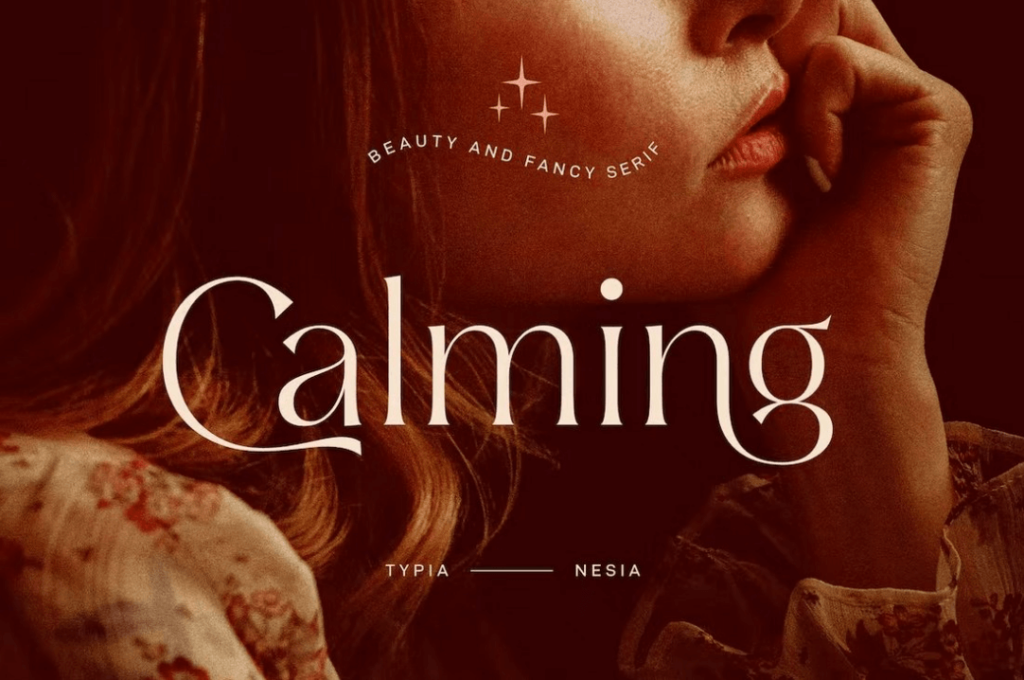
Calming — это красивый и элегантный шрифт, который поможет придать вашему дизайну легкость и индивидуальность. Шрифт идеально подходит для дизайна упаковки косметических продуктов. Вы также можете использовать его для брендинга, постов в социальных сетях и дизайна веб-сайтов.
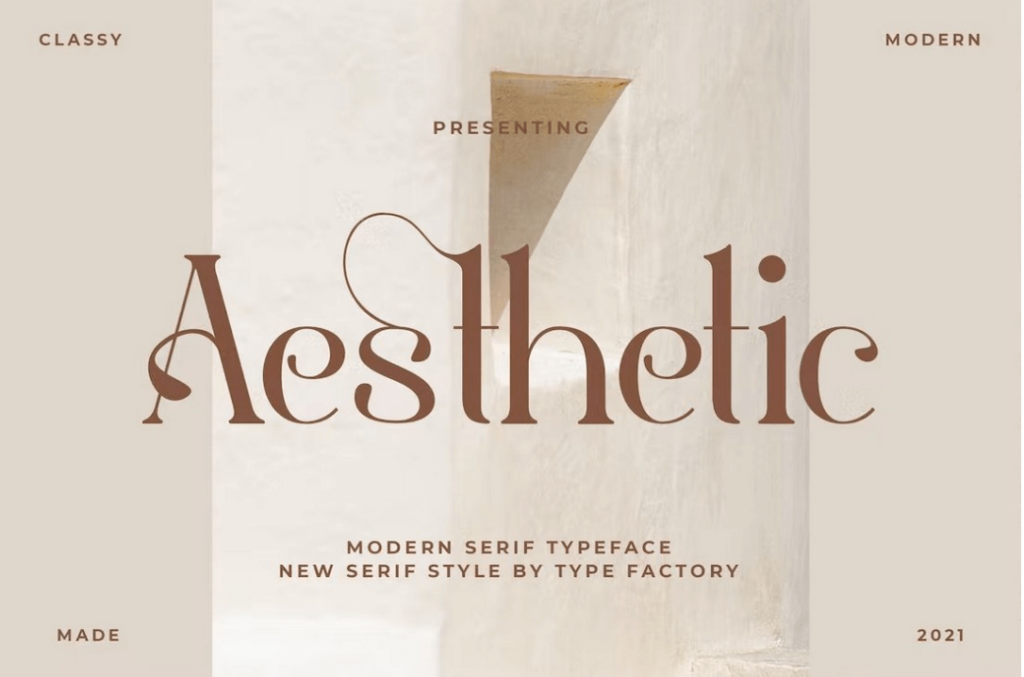
Шрифт Aesthetic имеет современный дизайн букв с засечками, смешанный с уникальными декоративными элементами. У шрифта есть как прописные, так и строчные символы. Вы можете использовать его для брендинга, обложек журналов и других проектов.
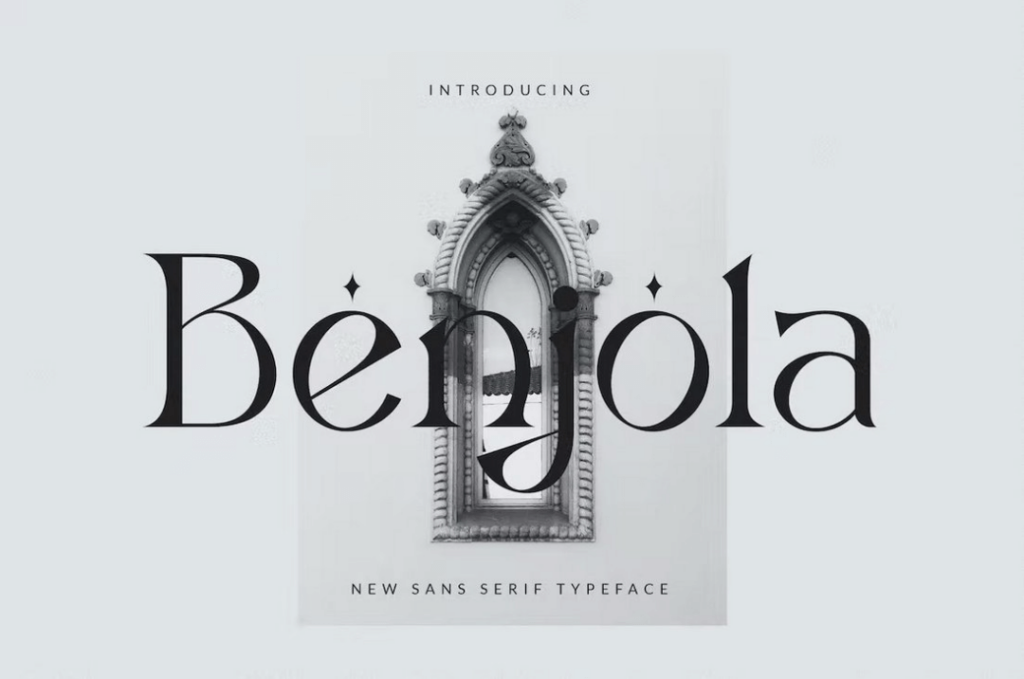
Benjola — это уникальный минималистичный шрифт, который выглядит современно и роскошно. Он поможет сделать логотипы вашего бренда роскошным, а дизайн упаковки или заголовок веб-сайта профессиональным.
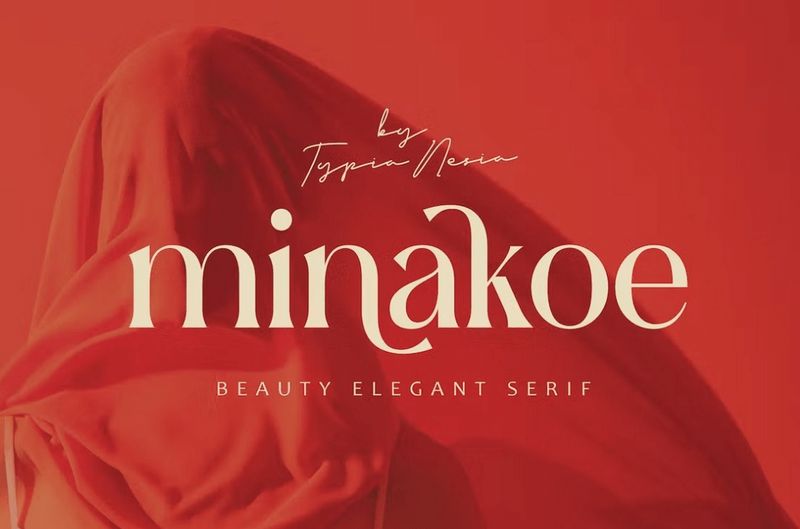
Шрифт Minakoe разработан с учетом проектов, которые посвящены моде и красоте. У шрифта красивый и элегантный дизайн букв, который позволит вам создать изящные дизайны. Он идеально подходит для этикеток продуктов, упаковки, логотипов, а также он хорошо будет смотреться в заголовках веб-сайтов.
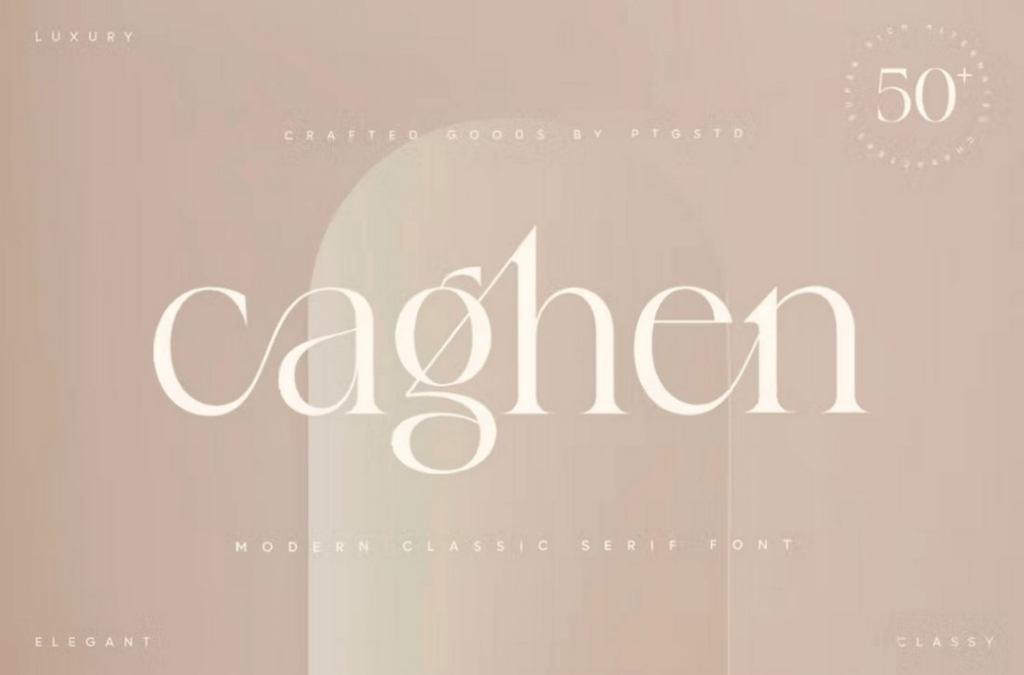
Caghen — это современный эстетичный шрифт с уникальным дизайном лигатуры курсивного стиля. Обычная версия шрифта идеально подходит для оформления заголовков веб-сайтов. У этого шрифта очень интересные лигатуры, которые можно использовать для создания рукописных элегантных надписей.